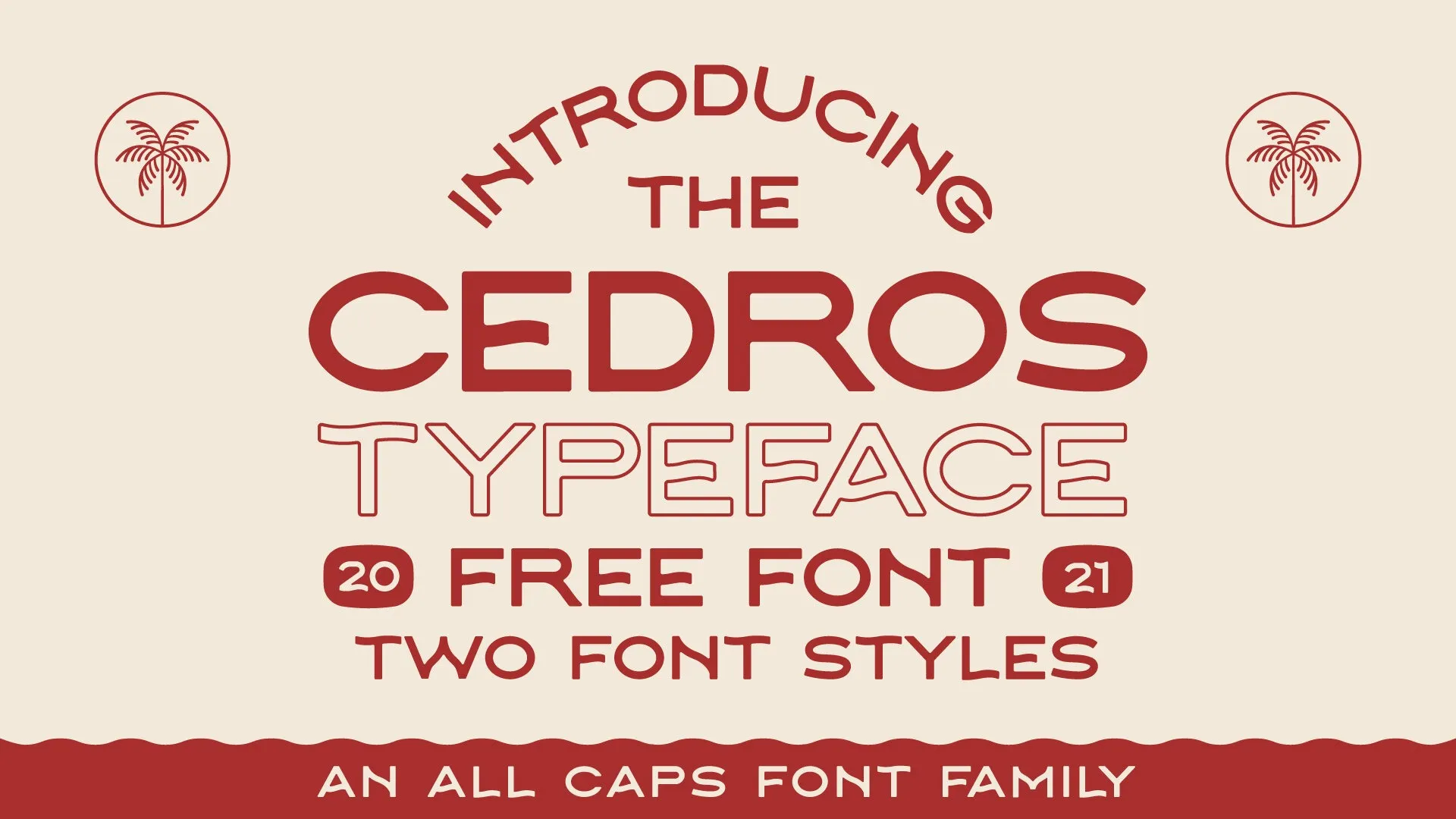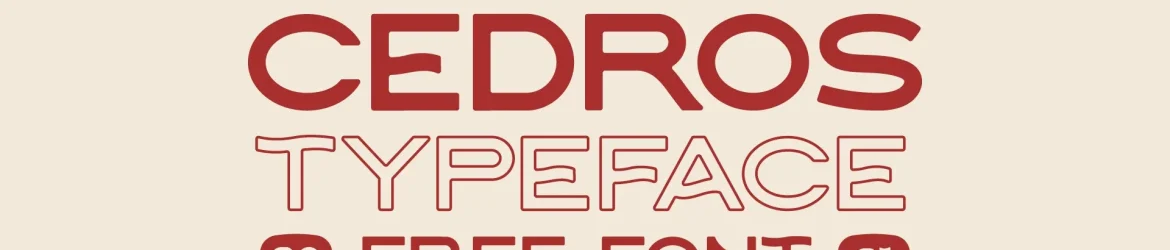
A Cedros Font é uma elegante e moderna fonte para sans serif criada por Adam Nienow. Com linhas simples e geométricas, ela proporciona um estilo contemporâneo e sofisticado que se adapta perfeitamente a diversas aplicações gráficas. Perfeita tanto para criação de projetos como logotipos, headlines ou letras grandes, também é uma ótima opção para capas de livros, revistas, cartazes e textos de citações. Sujeitosa à moda, a Cedros Font se destaca por sua simplicidade, oferecendo um contraponto interessante aos outros tipos de fontes. Ela é perfeitamente adequada para uma ampla variedade de projetos visuais em seu design, tornando-a uma opção valiosa tanto para designers profissionais quanto para iniciantes.